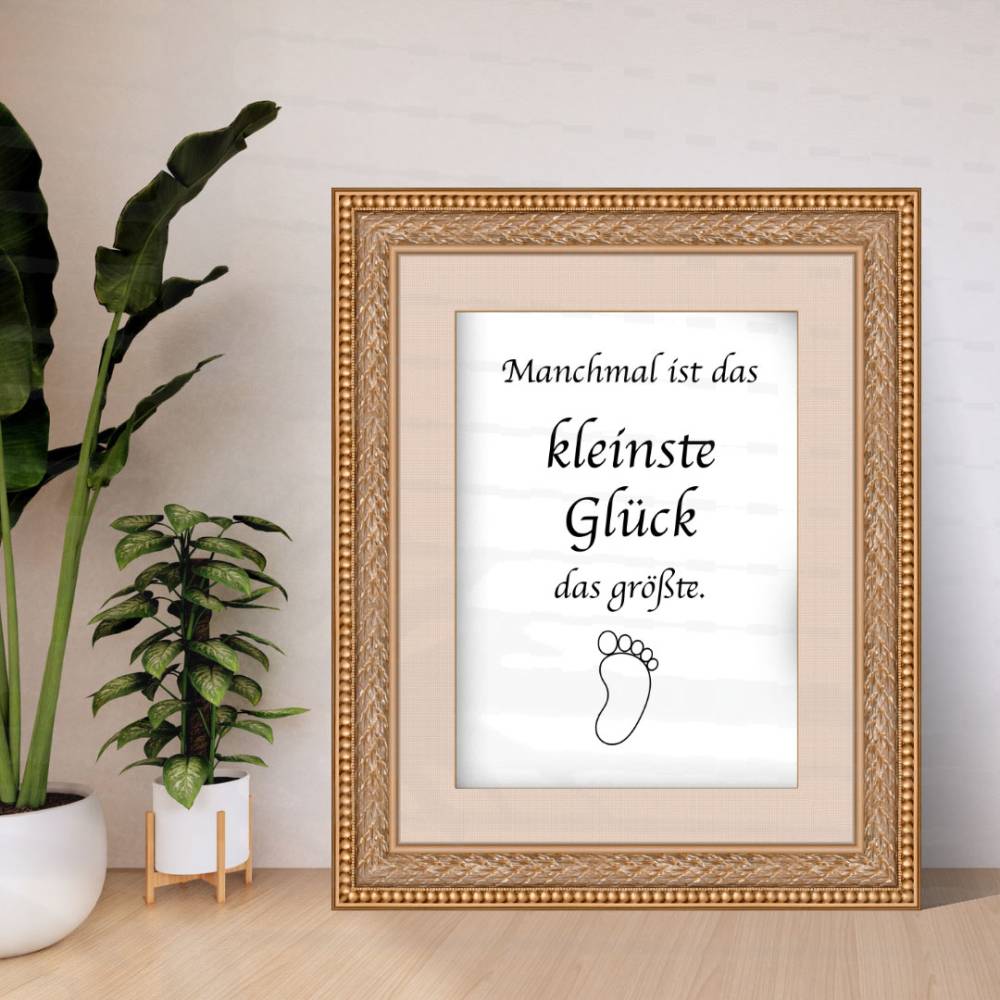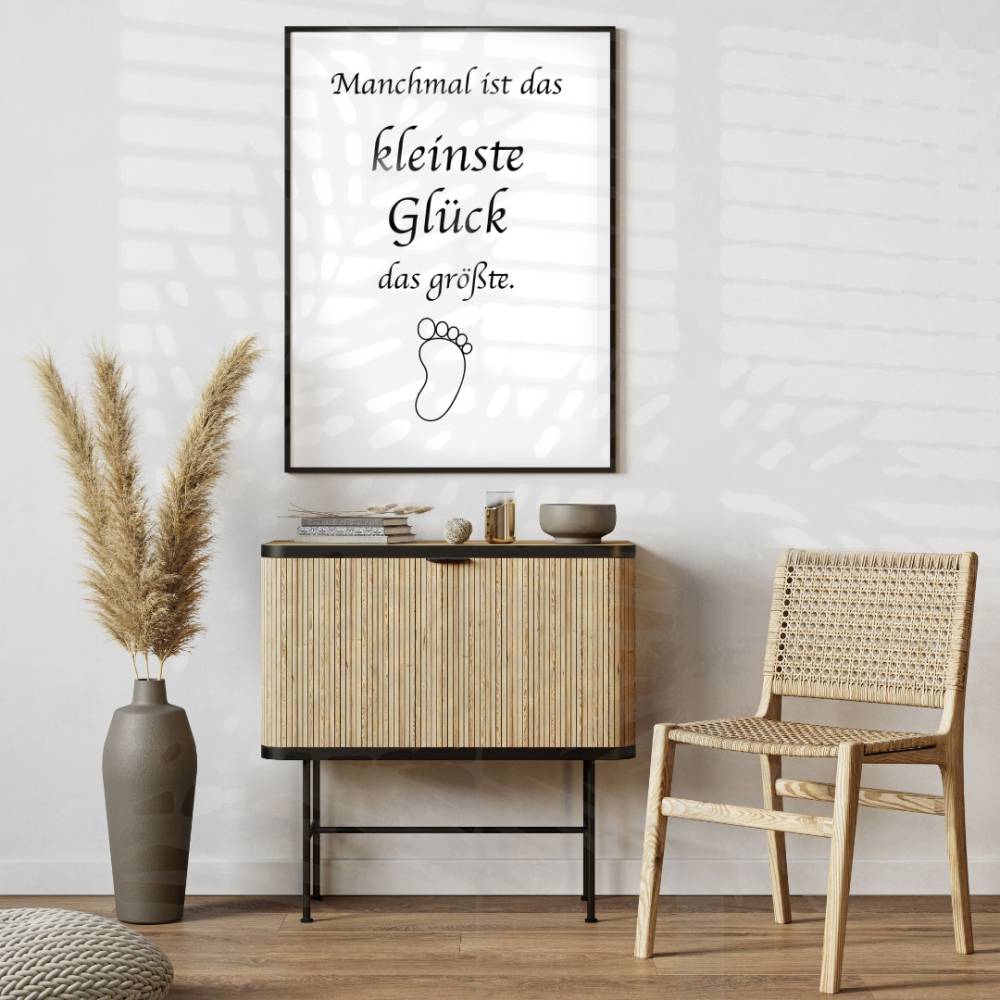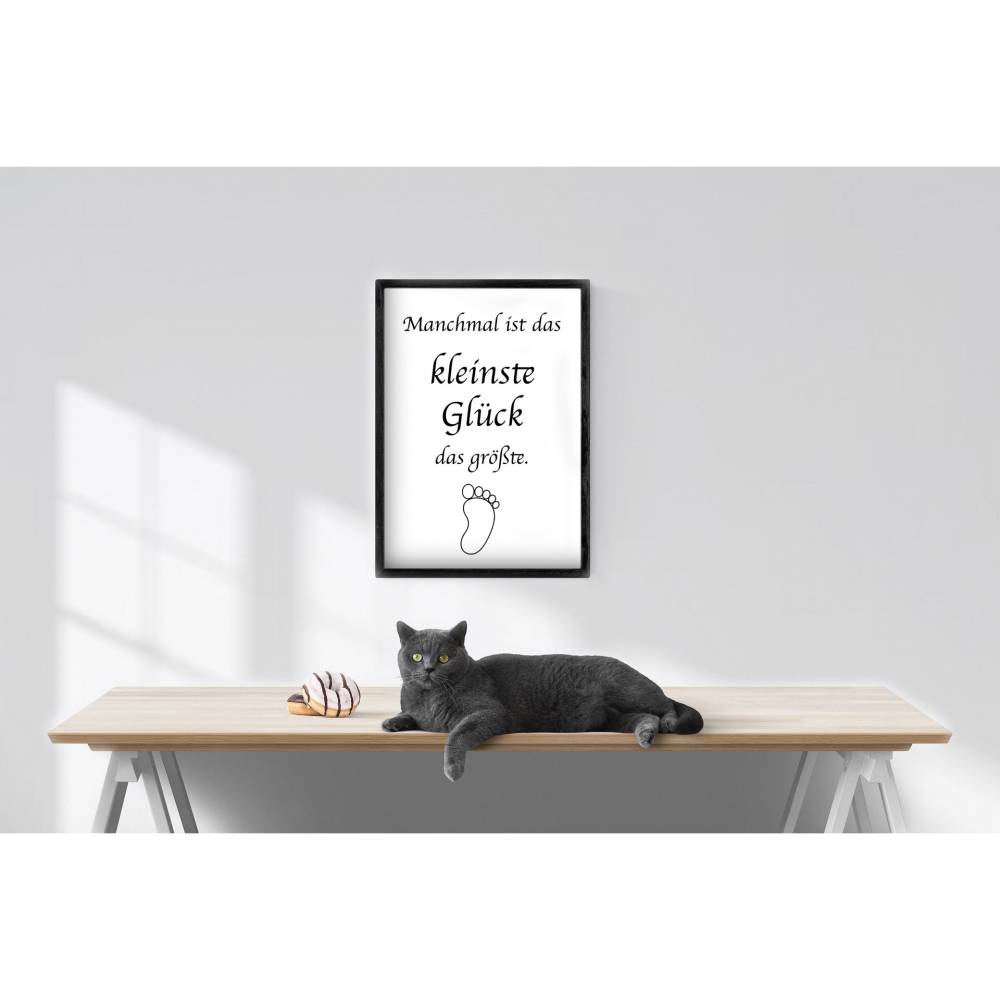
Poster DIN A4 – „Manchmal ist das kleinste Glück das größte“ | Spruchposter | Typografie | minimalistisch | schwarz-weiß
„Manchmal ist das kleinste Glück das größte.“
Ein liebevoll gestaltetes Spruchposter im DIN A4-Format, das dich täglich daran erinnert, wie wertvoll die kleinen Dinge im Leben sind. Dieses minimalistische Poster in Schwarz-Weiß bringt mit klarer Typografie und einem dezenten Symbol – einem kleinen, stilisierten Baby-Fußabdruck – genau diese Botschaft auf den Punkt.
Das Design wirkt modern und zeitlos zugleich. Es eignet sich perfekt als Wanddeko für Wohnzimmer, Schlafzimmer, Büro oder Kinderzimmer, aber auch als besonderes Highlight in einer Galeriewand, einem Flur oder Eingangsbereich.
Das Poster ist außerdem eine wundervolle Geschenkidee zur Geburt, Taufe, zum Muttertag, für die beste Freundin oder einfach für dich selbst – ein Ausdruck von Achtsamkeit, Liebe und Dankbarkeit.
– Design: Spruch in moderner Typografie + Symbol Babyfußabdruck